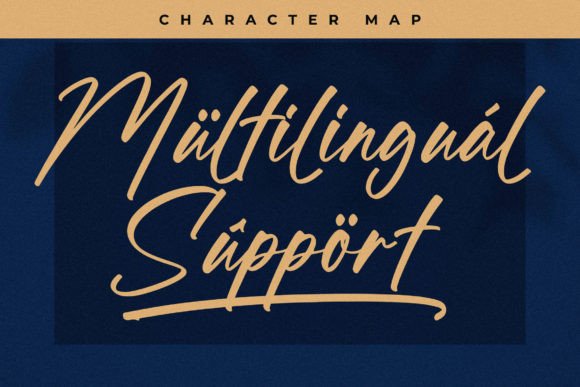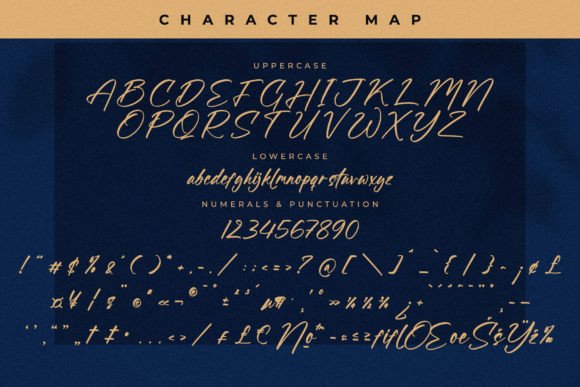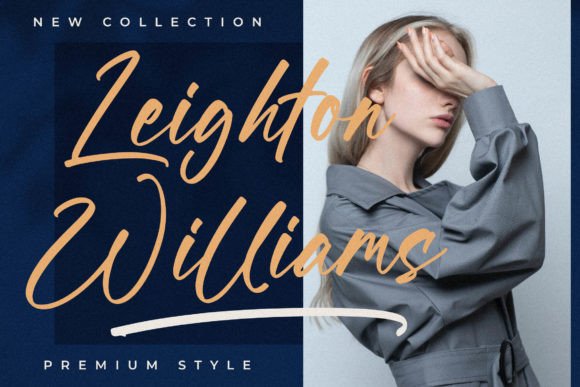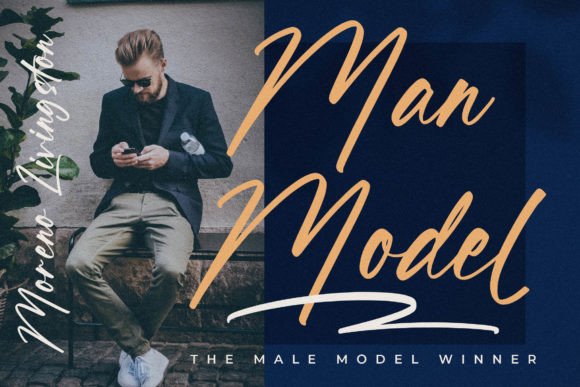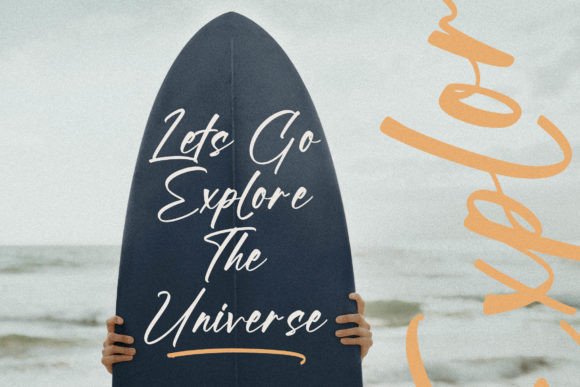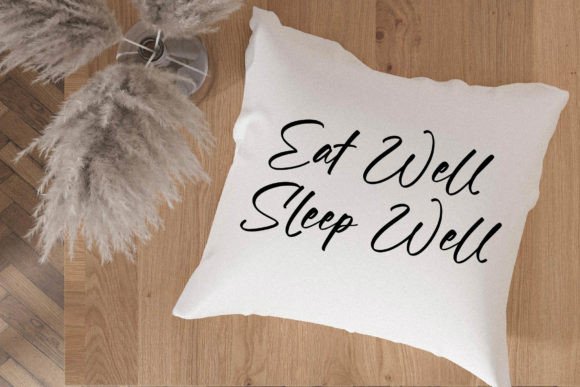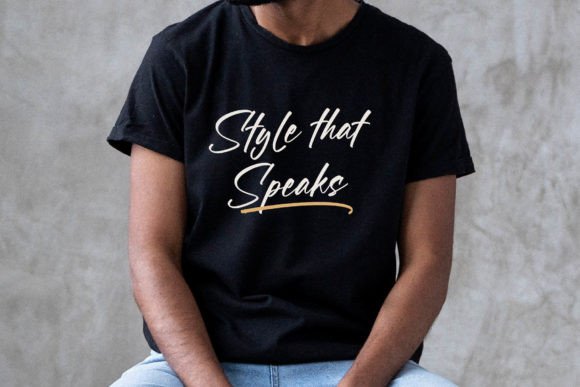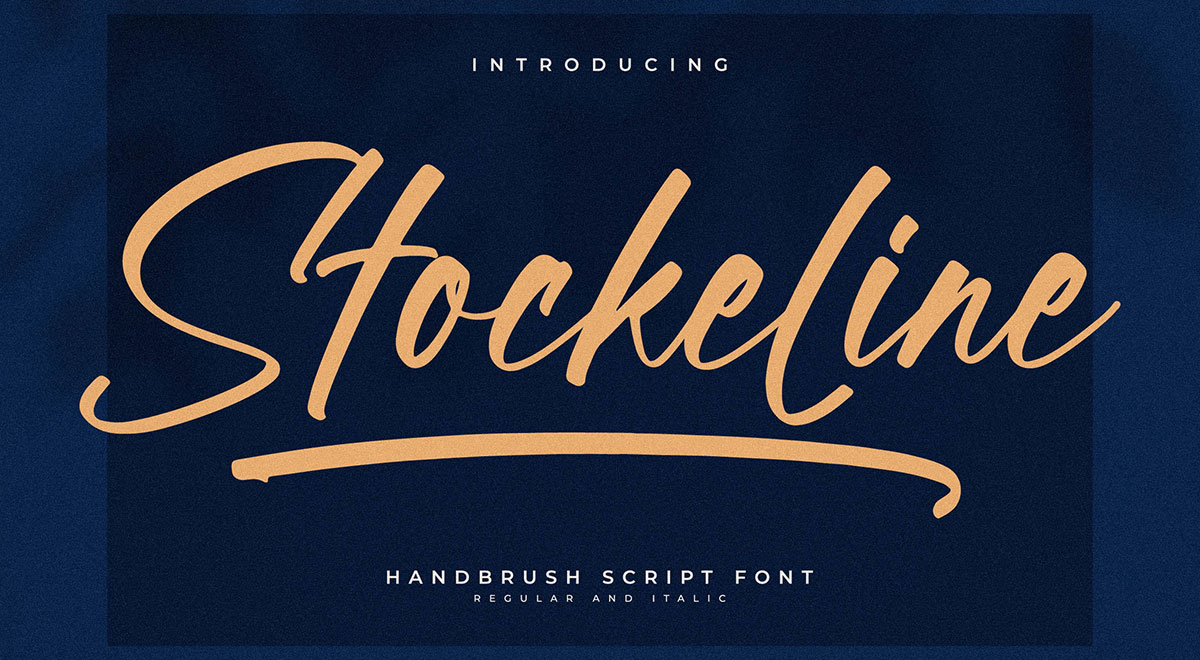
دانلود فونت Stockeline انگلیسی Font استاکلاین |
| ⭐ مجموعه فونت | دانلود فونت انگلیسی استاکلاین Font Stockeline استاکلاین ایتالیک Stockeline Italic |
| ⭐ توضیحات | Stockeline – Handbrush Script Font، از Glorytype Studio، مناسب برای هر پروژه ای مانند: لوگو، پروژه های برندسازی، طراحی لوازم خانگی، بسته بندی محصول، لیوان، نقل قول، پوستر، کیسه خرید، تی شرت، جلد کتاب، کارت نام، کارت دعوت، کارت پستال، برچسب، عکاسی، واترمارک، رویدادهای خاص، و تمام پروژه های دوست داشتنی شما که نیاز به طعم و مزه فیلمنامه زیبا دارند. |